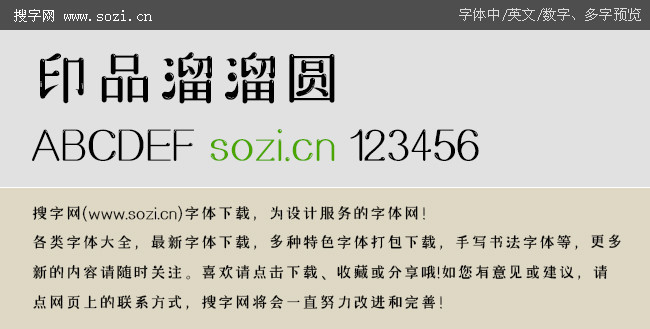
印品溜溜圓
搜字網(wǎng)給大家提供一款印品溜溜圓中文字體下載,該字體整體圓潤(rùn)飽滿,筆畫較粗狂,字體內(nèi)部空間較小,筆畫末端做圓弧狀處理,樸拙中不失靈動(dòng),具有極強(qiáng)的時(shí)尚感。適用于海報(bào)設(shè)計(jì)、包裝設(shè)計(jì)、商業(yè)廣告等廣告設(shè)計(jì)。